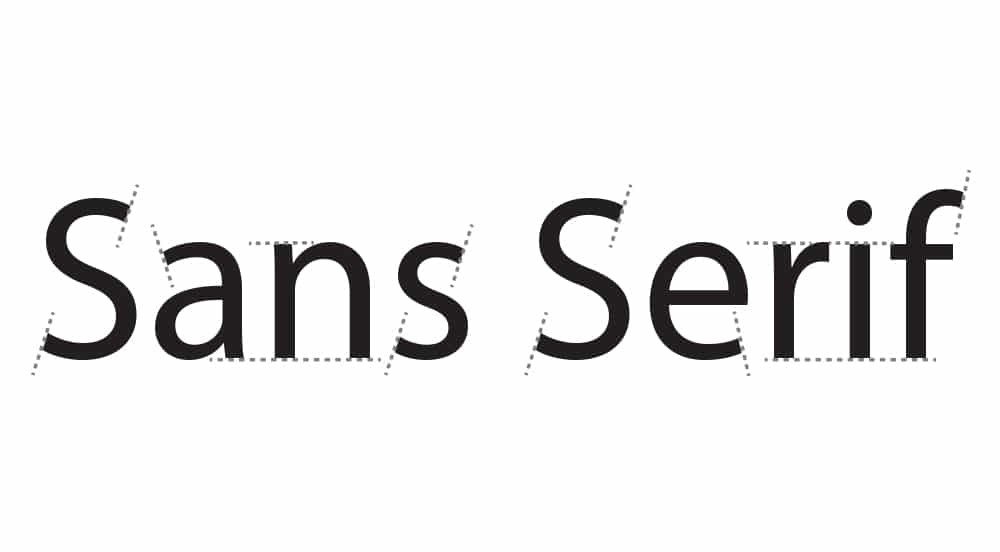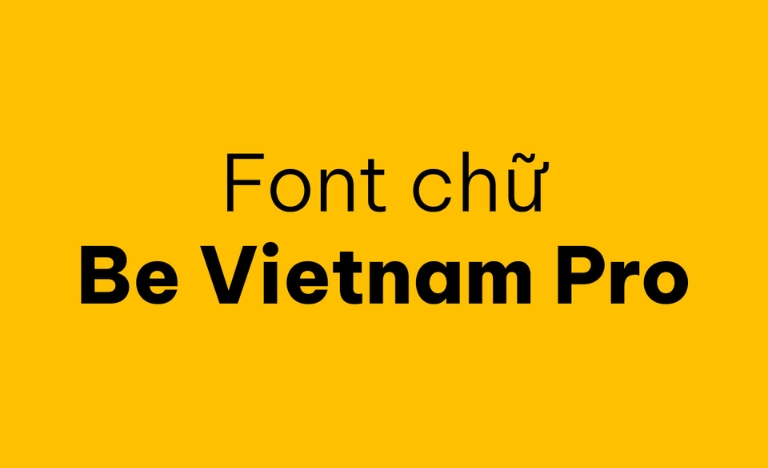
Font Sans-serif là lựa chọn ưu tiên trong thiết kế hiện đại nhờ cấu trúc tối giản, giúp văn bản trở nên thông thoáng và dễ đọc trên mọi nền tảng. Việc sở hữu bộ tải font Sans-serif chuẩn giúp các kiến trúc sư và nhà thiết kế trình bày hồ sơ dự án, bản vẽ kỹ thuật một cách chuyên nghiệp, tránh các lỗi hiển thị ký tự đặc trưng của tiếng Việt.
Đặc điểm thẩm mỹ của dòng phông chữ Sans-serif hiện đại
Điểm nhận diện đặc trưng của dòng phông này chính là việc loại bỏ các nét gạch nhỏ ở đầu và cuối các ký tự, tạo nên vẻ ngoài gọn gàng và vững chãi. Các bộ font Sans-serif Việt hóa thường sở hữu cấu trúc hình học cân đối, mang lại cảm giác năng động và trẻ trung cho bản thiết kế. Việc xử lý dấu thanh tiếng Việt tỉ mỉ giúp các dấu hỏi, ngã, nặng phối hợp hài hòa với thân chữ, duy trì nhịp điệu thị giác ổn định và sự mạch lạc cho toàn bộ văn bản.
Sự ổn định của Sans-serif còn thể hiện qua khả năng hiển thị rõ nét ở nhiều kích thước khác nhau. Dù được sử dụng trên màn hình kỹ thuật số độ phân giải cao hay in ấn trên các vật liệu xây dựng thực tế như tấm panel, alu, inox, các nét chữ vẫn giữ được sự sắc sảo. Đây là giải pháp phù hợp để thể hiện tư duy thiết kế hiện đại, tinh gọn, rất ăn ý với các phong cách kiến trúc công nghiệp hoặc tối giản đang dẫn đầu xu hướng hiện nay.
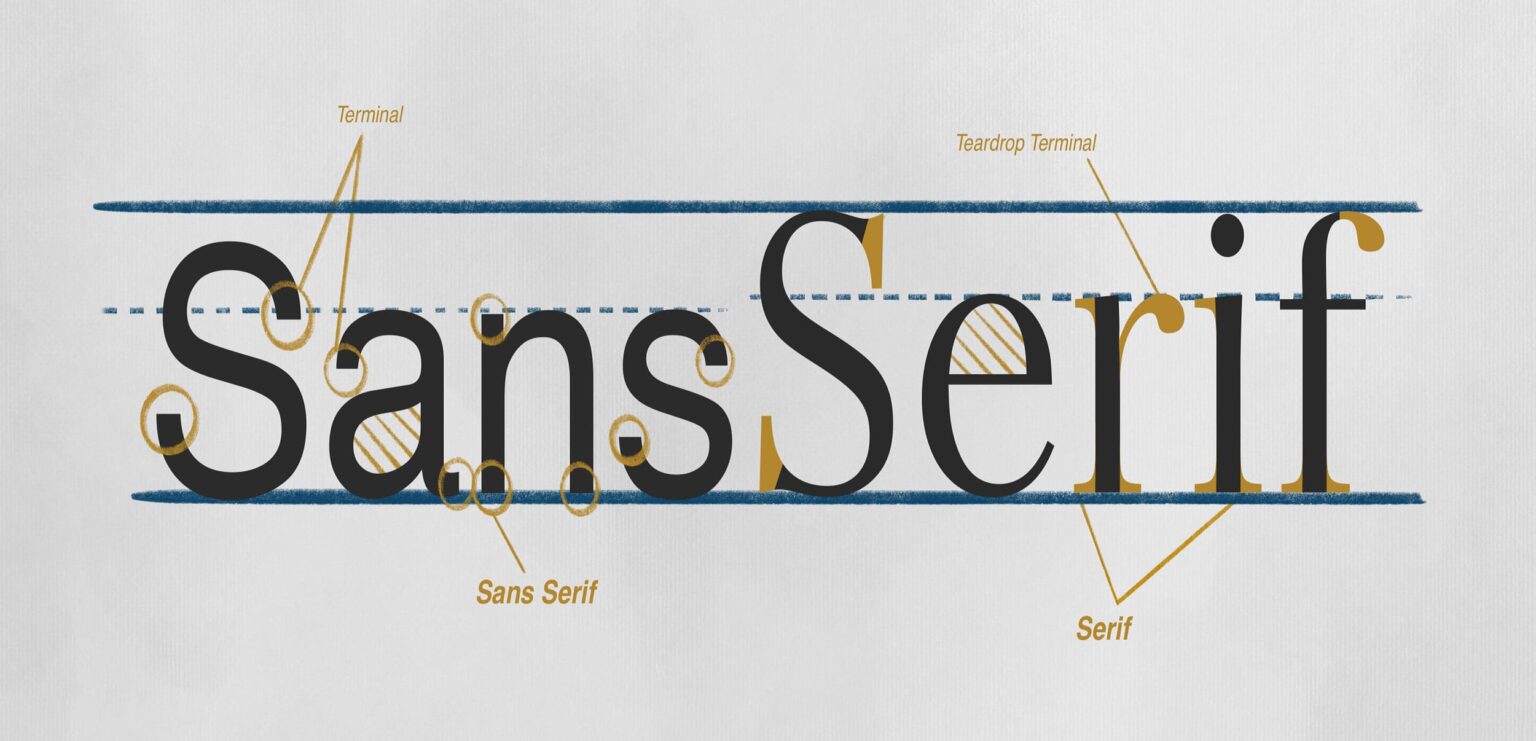
| Phân loại phong cách | Sans-serif (Không chân) / Geometric / Humanist |
| Dòng font tiêu biểu | Roboto, Montserrat, Open Sans, MS Sans Serif |
| Mục đích phù hợp | Bản vẽ CAD, Profile dự án, Website, Branding |
Tư vấn lựa chọn: Để bản thiết kế đạt được hiệu quả thị giác ổn định, bạn nên phối hợp giữa các độ đậm nhạt khác nhau trong cùng một gia đình font. Sử dụng các biến thể Bold cho đề mục lớn và kiểu Regular cho nội dung chi tiết sẽ giúp hồ sơ dự án của bạn có sự phân cấp thông tin khoa học và dễ theo dõi hơn.
03 Ứng dụng phông chữ không chân vào thiết kế kiến trúc
Nhờ diện mạo khoa học và dễ tiếp nhận, việc sử dụng các kiểu chữ từ tải font Sans-serif mang lại giá trị thực tế cao trong quá trình triển khai dự án hiện đại:
- Hệ thống nhận diện cho Homestay & Nhà lắp ghép: Những nét chữ không chân rất ăn ý khi xuất hiện trên biển hiệu gỗ hoặc alu phủ màu. Phông chữ này giúp không gian toát lên vẻ chỉn chu, hiện đại và cực kỳ thân thiện với du khách yêu thích lối sống xanh.
- Ghi chú kỹ thuật trên bản vẽ AutoCAD: Độ rõ nét của Sans-serif hỗ trợ đắc lực cho kỹ sư khi trình bày các thông số về vật liệu panel, kết cấu thép hay chi tiết lắp ghép, giúp đội ngũ thi công tại hiện trường tra cứu thông tin nhanh chóng và chính xác.
- Hồ sơ năng lực và báo cáo dự án: Sử dụng tải font MS Sans Serif hoặc các dòng tương đương cho các bảng tính dự toán giúp các con số hiển thị tách bạch, rõ ràng, hạn chế tối đa việc nhầm lẫn số liệu khi làm việc với chủ đầu tư.
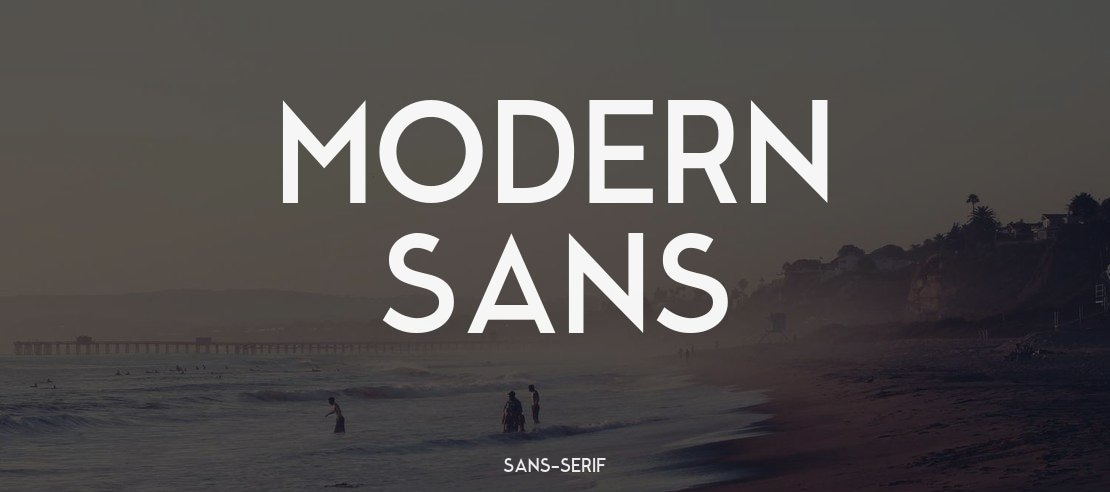
03 Lưu ý để bố cục phông chữ Sans-serif đạt độ rõ nét cao
Để khai thác hiệu quả vẻ đẹp trung tính và tính năng đa năng của bộ phông này, người thiết kế nên lưu tâm một số lưu ý kỹ thuật sau:
- Kiểm soát khoảng cách dòng: Với cấu trúc chữ hiện đại, bạn nên để khoảng cách dòng thoáng một chút (khoảng 1.4 – 1.6 lần cỡ chữ) để văn bản không bị bết dính, giúp người đọc cảm thấy thoải mái hơn khi tiếp nhận thuyết minh dự án dài.
- Sử dụng độ đậm (Weight) phù hợp: Hãy tận dụng các biến thể đậm của download font Sans-serif cho các tiêu đề chính để tạo độ nhấn thị giác mạnh. Các ghi chú nhỏ trên bản vẽ kỹ thuật nên sử dụng nét mảnh để giữ cho bố cục không bị rối mắt.
- Tính đồng bộ thương hiệu: Hãy duy trì sử dụng một nhóm font Sans-serif xuyên suốt từ trang web giới thiệu giải pháp nhà container đến hồ sơ báo giá thực tế để tạo nên sự nhất quán trong hình ảnh chuyên nghiệp của đơn vị.